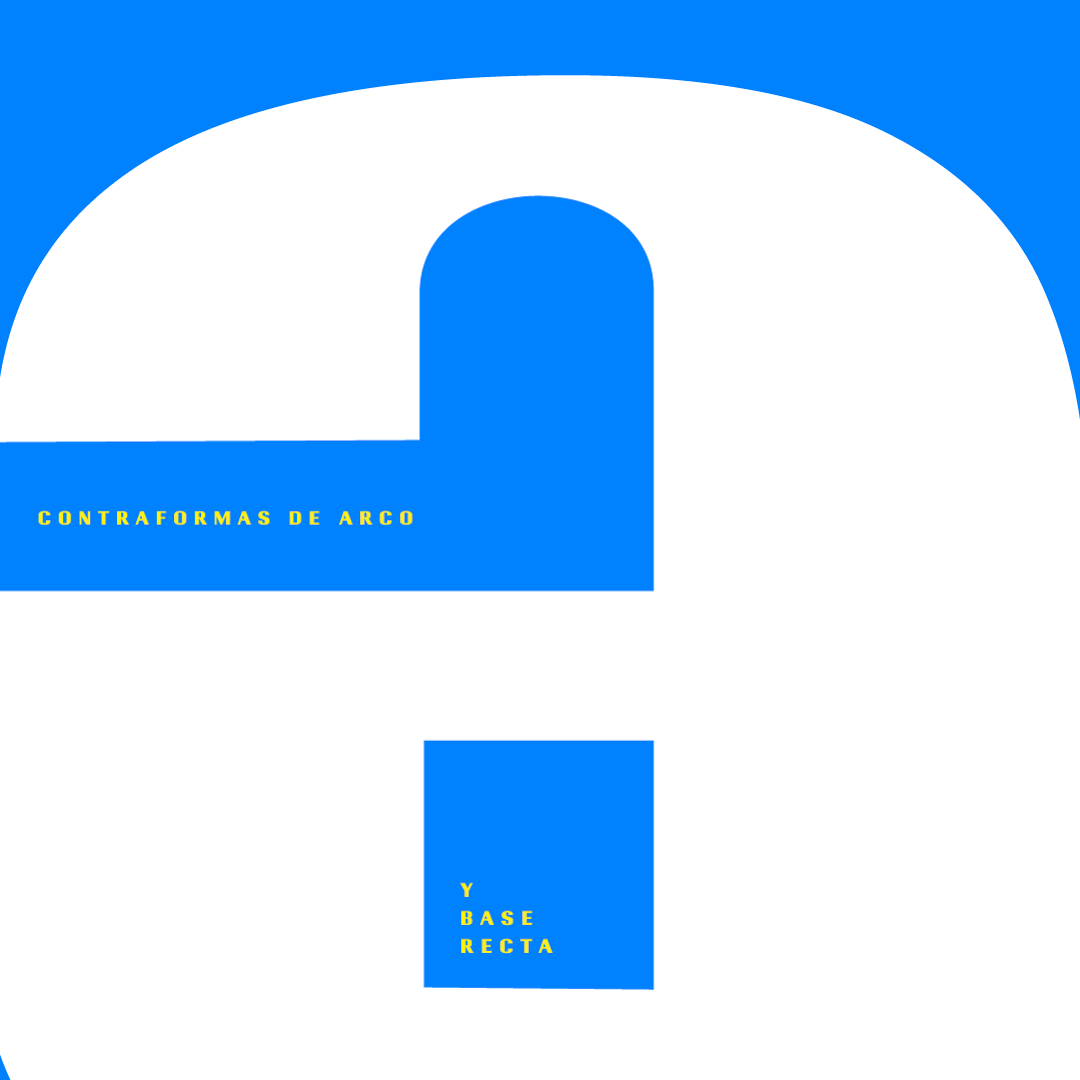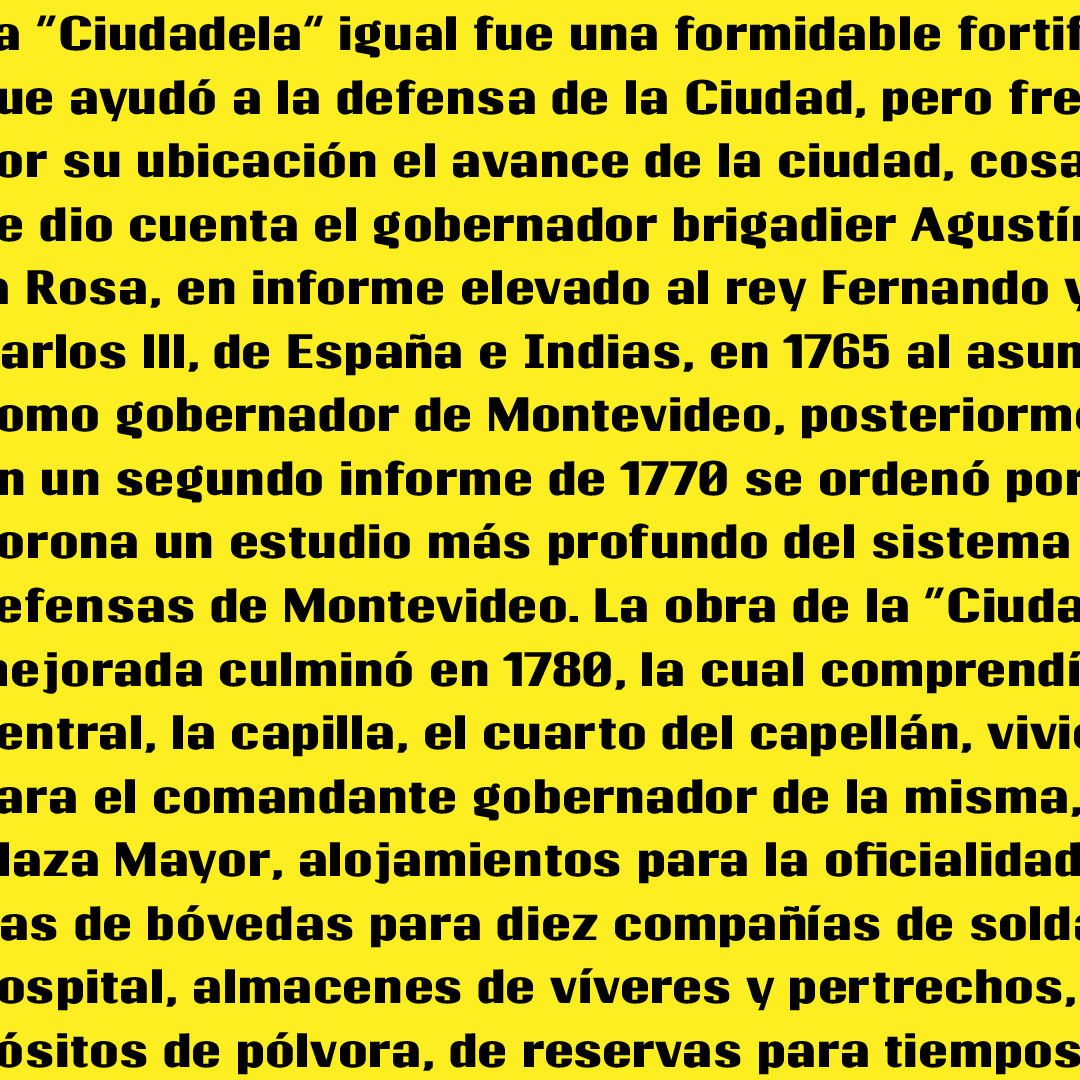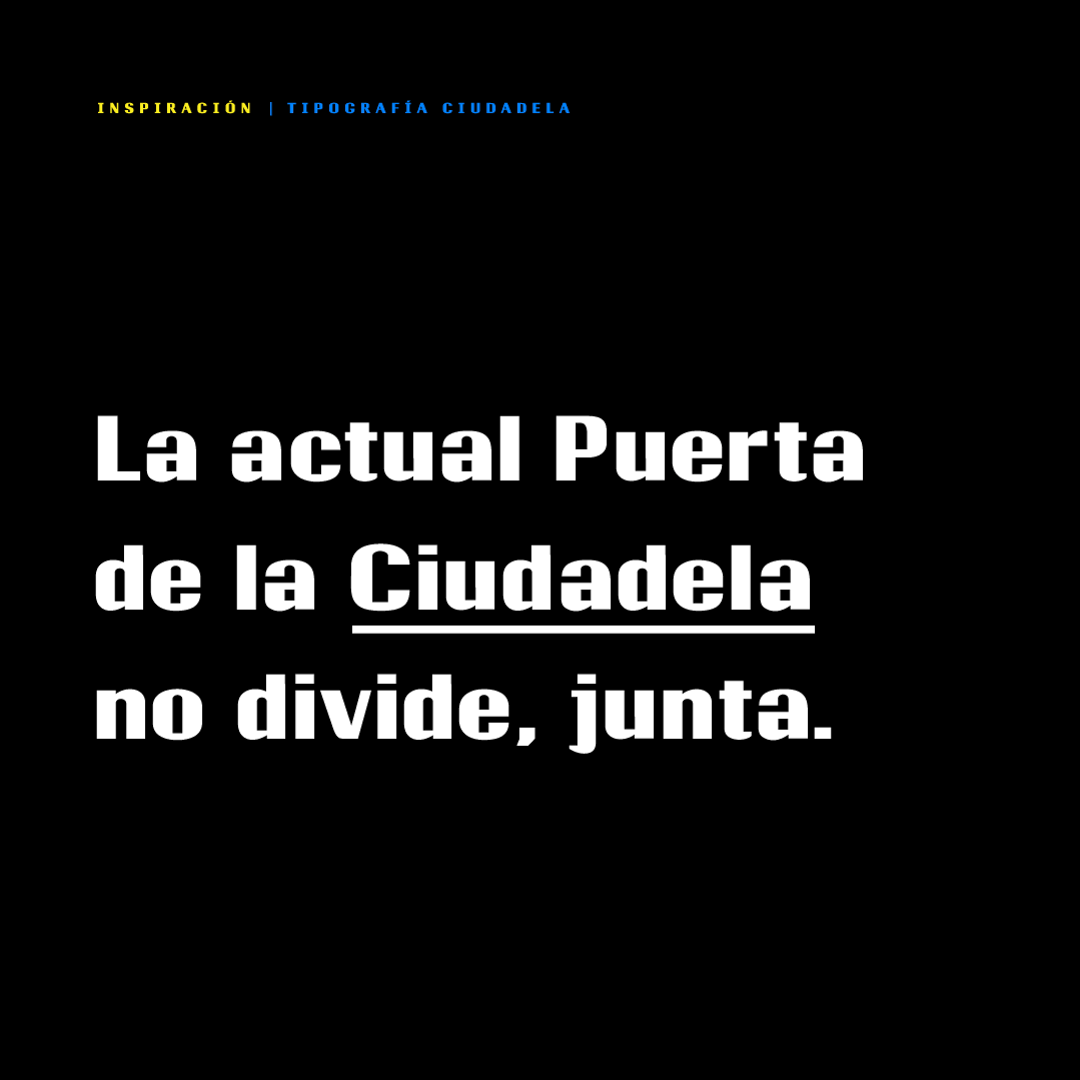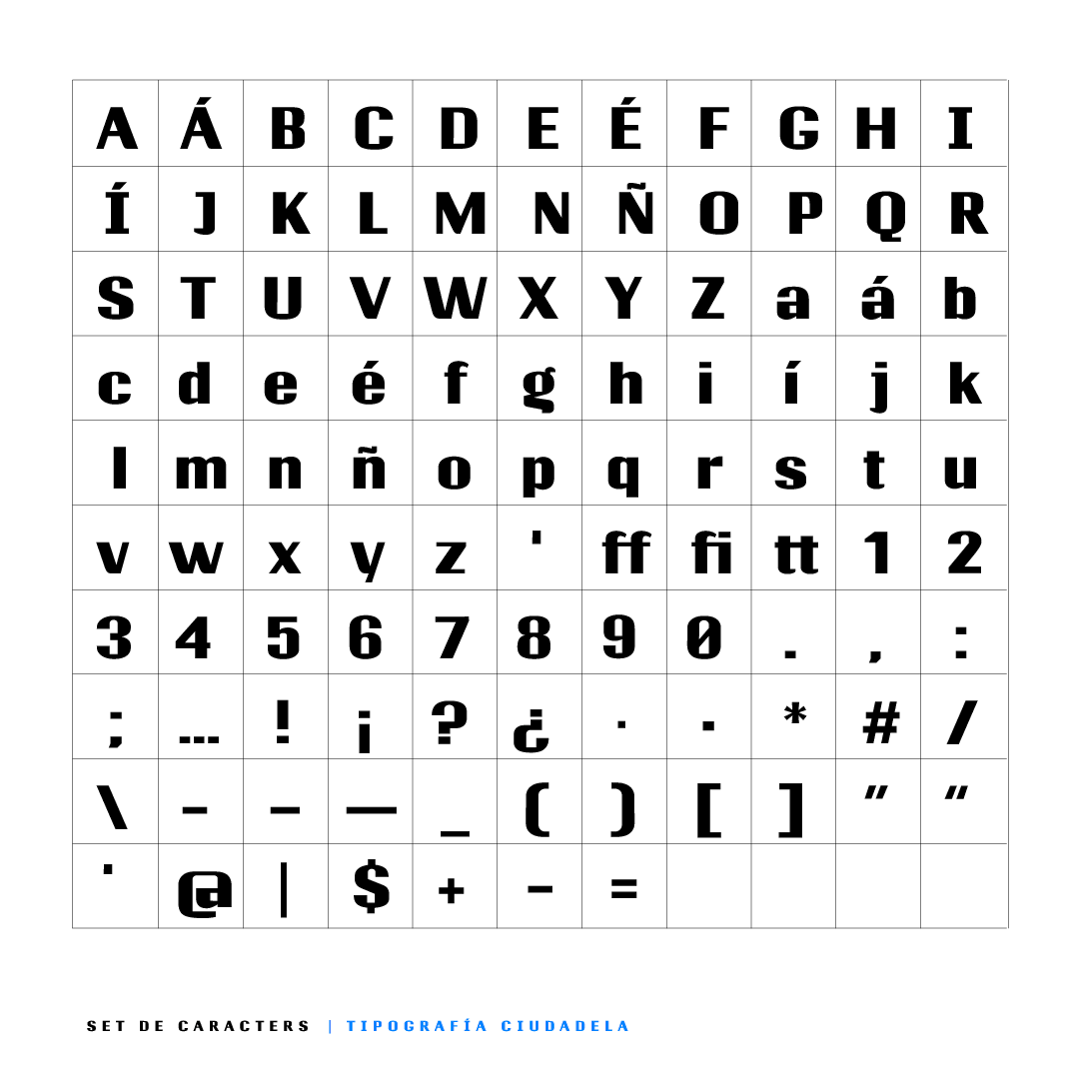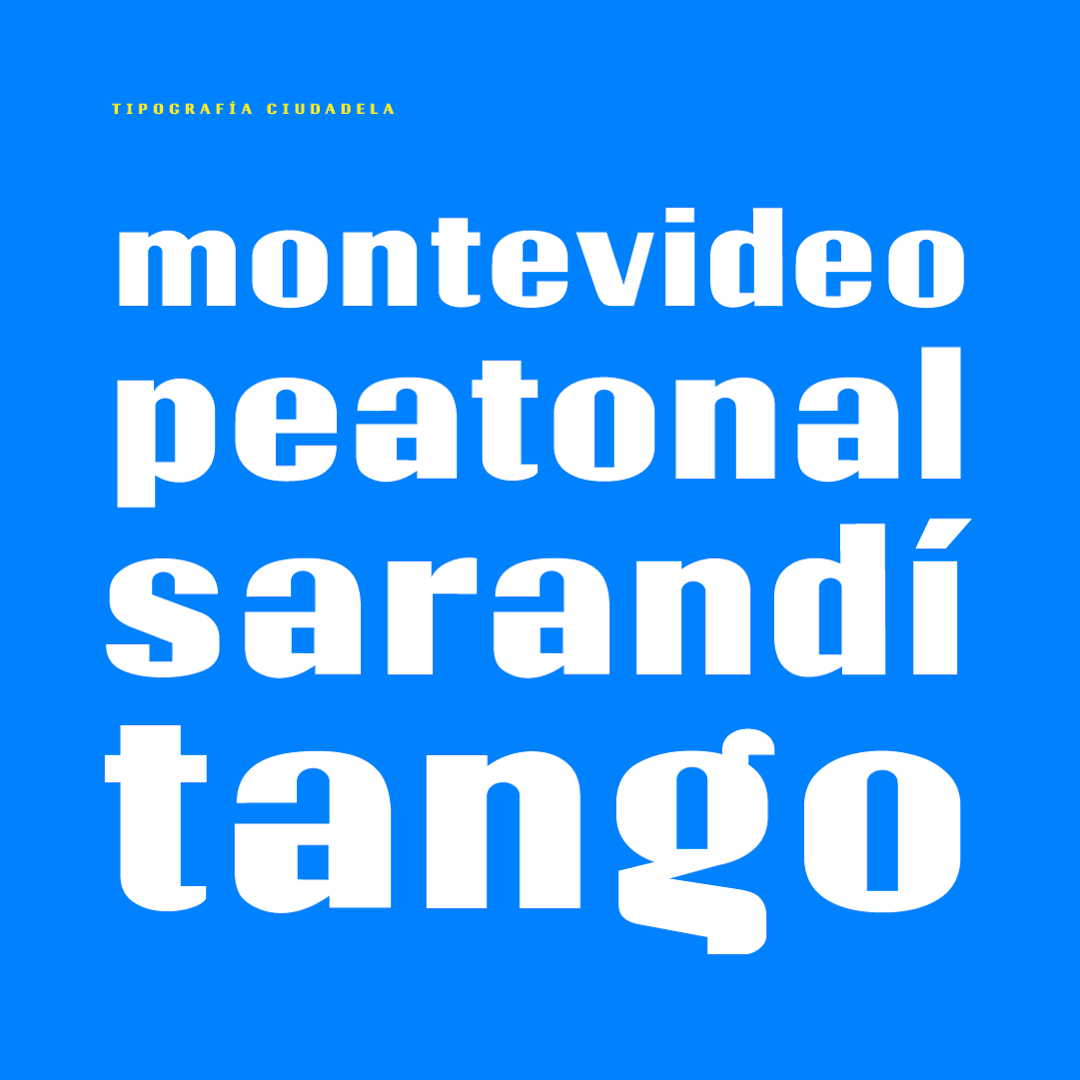
Inspirada en la histórica Puerta de la Ciudadela de Montevideo, esta tipografía display retoma las formas geométricas de su arquitectura y el ritmo contundente de los bloques que alguna vez delimitaron la ciudad. Sus contraformas revelan arcos en la parte superior y bases rectas, mientras que los umbrales de cada carácter se mantienen estrechos, evocando la solidez y el carácter monumental de la estructura original.
El proceso comenzó buscando inspiración en la geometría del monumento histórico, y poco a poco fue tomado su propia impronta. Los dibujos a mano sentaron las bases para definir trazos finos y gruesos, los ritmos, velocidades y sus contraformas caracterísiticas.